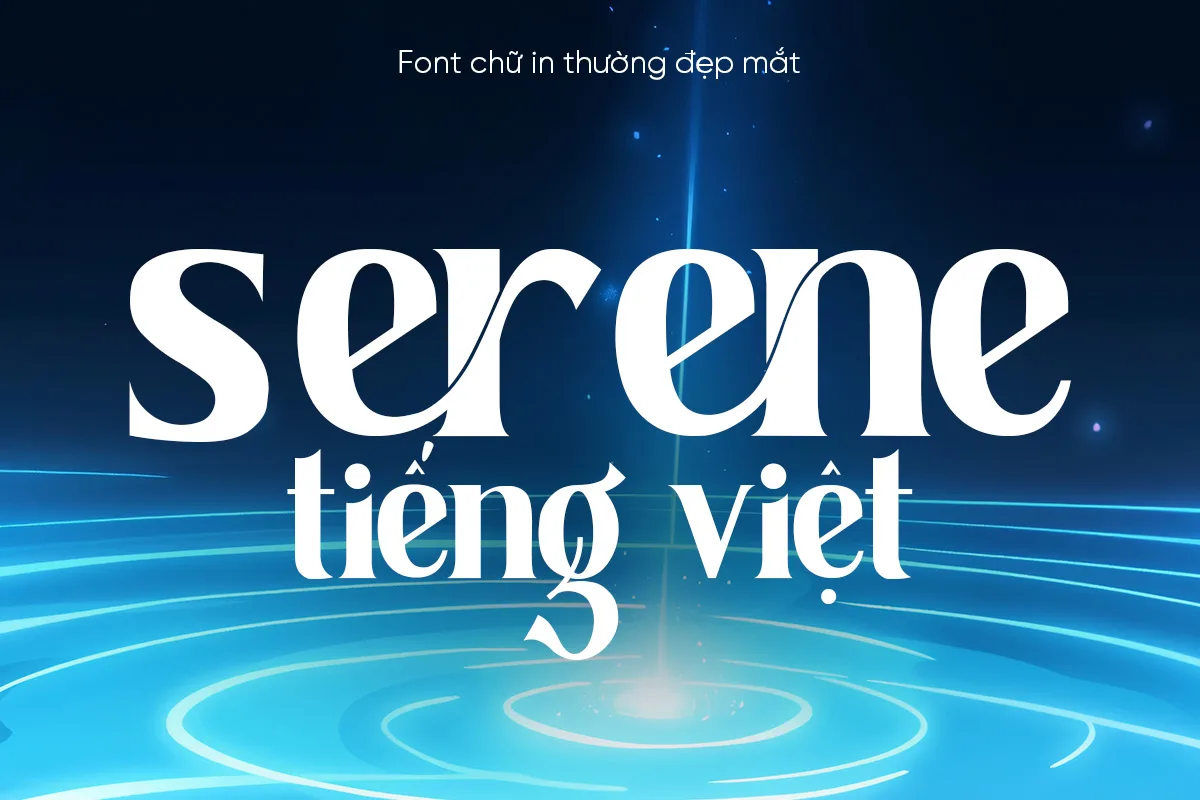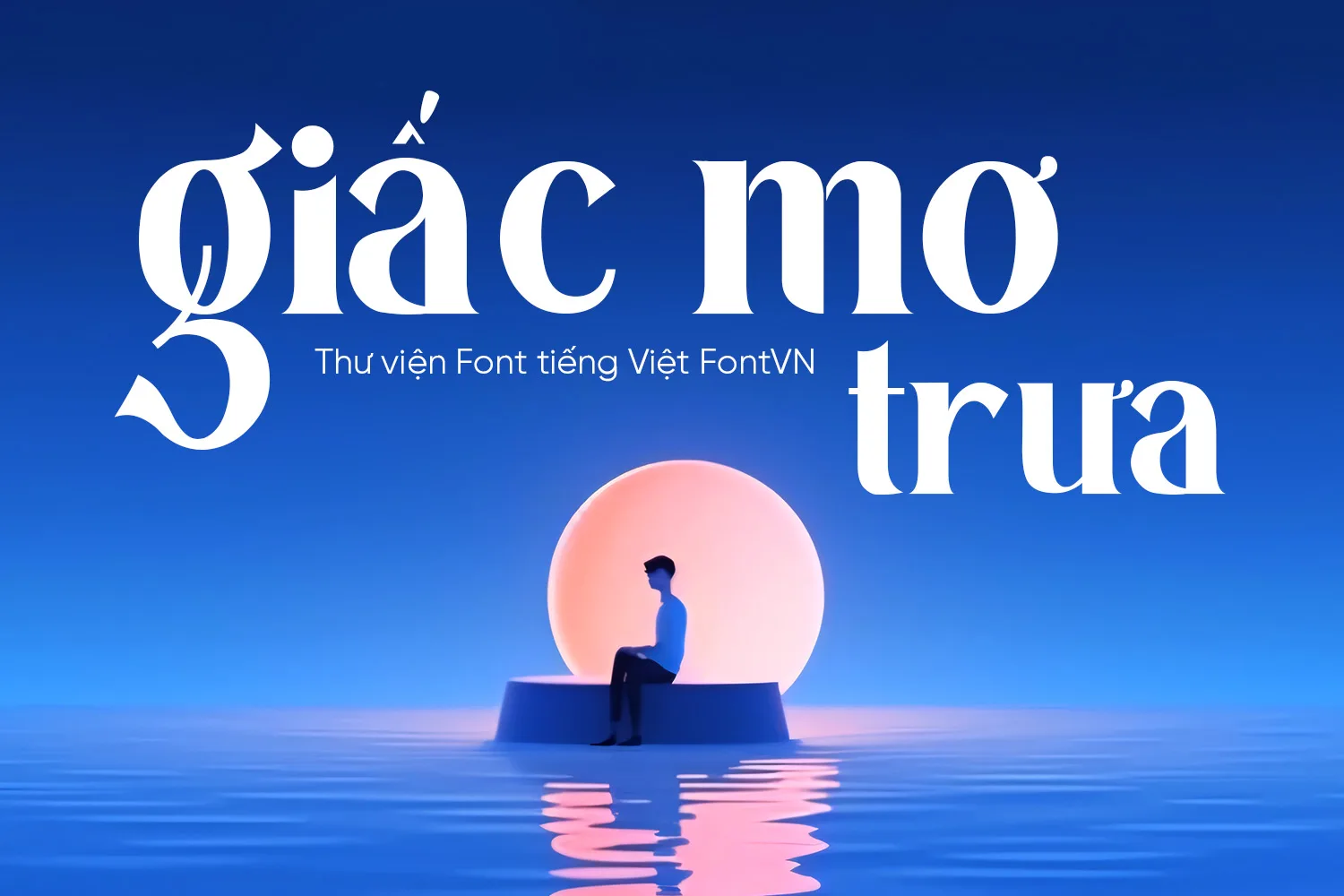
DVN Serene tiếng Việt – Font Serif Thanh Lịch Cho Thiết Kế Editorial & Branding
DVN Serene là font serif mang phong cách hiện đại với những đường nét thanh mảnh, độ tương phản cao và các chi tiết được tinh chỉnh tinh tế. Phiên bản Việt hóa đầy đủ giúp font hiển thị hoàn hảo tiếng Việt, phù hợp cho các dự án thiết kế yêu cầu sự sang trọng, tối giản và đậm chất nghệ thuật.
Điểm nổi bật của DVN Serene nằm ở hệ thống chữ thường (Lowercase) được thiết kế độc đáo, mang lại cảm giác mềm mại nhưng vẫn đầy cá tính. Font tạo nên vẻ đẹp cao cấp cho các bố cục editorial, tạp chí, thời trang và nhận diện thương hiệu, đồng thời vẫn đảm bảo khả năng đọc tốt ở nhiều kích thước.
DVN Serene là lựa chọn lý tưởng cho thiết kế logo, branding, poster, bìa sách, bao bì sản phẩm, lookbook, social media, website, giao diện UI cao cấp và các dự án in ấn cần một phong cách thanh lịch, khác biệt và hiện đại.